Однажды, смотря на матричное табло, я подумал, что было бы не плохо, если бы смена текста была анимированной. Стало интересно попробовать. Прототип анимации.
Изначально думал, что для реалистичной анимации движения точек должны быть с ускорением и торможением, но их реальный ход на экране оказался не таким уж большим и реальный эффект был совсем не заметен, кроме того, финальный пиксель получался как бы с задержкой, поэтому, отказался. Если при переходе между символами количество точек разное, то исчезающие точки складываются в последнюю нового символа, а добавляющиеся идут от последней точки начального символа.
Разработка точечного шрифта
Каждый символ описывается координатами точек. Первые 10 символов, представляющих цифры, плюс пара дополнительных для показа градусов, я сделал самостоятельно. За основу символов изображения погоды я взял шрифт, содержащий иконки символов погоды и руками их доработал в редакторе FontCreator. Для того, чтобы анимация символов не выглядела как беспорядочное перемещение точек от одних координат к другим, их необходимо расположить в определённом порядке, чтобы неизменяемые части при переходе оставались на тех же местах, а изменяемые менялись желательно так, чтобы меньше пересекаться с другими точками при движении. FontCreator позволяет при редактировании символа указать индекс каждой точки. Каждая точка у меня это матрица восьмибитных полутонов. Для небольшого размера такие матрицы я подготовил руками, после 8 рисуется автоматически из заполненных кругов понижая яркость от центра к краю.
Не смотря на размеры моих символов 7х14, они очень хорошо масштабируются. Один и тот же шрифт я использовал для больших цифр и для цифр меньшего размера и это смотрелось заметно лучше, чем обычные варианты, предлагаемые готовыми библиотеками для микроконтроллеров.
Применение в часах
Первое же место, где можно применить этот шрифт, конечно же - часы. Как раз понадобилось на замену сделать что-то, чтобы было удобно с дивана смотреть. Предыдущий опыт с часами у меня уже был, там тоже был мой эксперимент с анимированным шрифтом. Там использовался шрифт на кривых Безье, когда каждая цифра описывалась ровно 3-мя кривыми. Впоследствии, я развил тему редактора таких шрифтов и эффектов с ними, но так и не воплотил это в какую‑то законченную библиотеку. Надо сказать, постоянная анимация секунд несколько отвлекает, взгляд прямо таки залипает на ней. Поэтому, в новых часах секундам отведено намного меньше места, надо близко подойти, чтобы их посмотреть.
Морфинг
Для анимационного перехода одного символа в другой выполняется несколько шагов. Создаётся два массива координат точек каждого символа: из которого происходит преобразование и в который происходит преобразование. Затем, количество элементов в этих массивах выравнивается, дополняя недостающие элементы размножением последнего элемента в соответствующем массиве. Функция, выполняющая преобразование, расчитывает сдвиг каждой точки по линии от старых координат к новым в зависимости от параметра `t ∈ [0, 1]`, где `t = 0` означает координаты исходного символа, а `t = 1` - координаты конечного символа. Параметр `t` расчитывается по времени так, чтобы весь промежуток от 0 до 1 пройти за половину секунды. Начальная точка отсчёта подбирается за пол секунды до наступления следующей секунды.
Перепробовал несколько разных дисплеев. В итоге, пришёл к выводу, что если хочется часы смотреть ночью, то засветка должна быть минимальная, а лучше никакая. Все хоббийные дисплеи, что прошли через мои руки, имели сильную проблему засветки, кроме OLED. Засветка становится важным критерием, когда часы планируется видеть ночью, когда никакого другого света, кроме как от часов, нет. К сожалению, с OLED дисплеями проблема, что трудно найти подходящий по размеру, разрешени и цене. Разрешение дисплея не должно быть сильно большим, памяти на виртуальный экран не хочется тратить много, размеры же, наоборот, хочется побольше, чтобы можно было изображение издалека видеть.
Я воспользовался тем, что информация на экране может быть разделена пополам -- с одной стороны часы, с другой минуты. Таким образом, экран часов состоит из двух OLED дисплеев размером 1,5" и разрешением 128х128 каждый. OLED SSD1351. На переднем фоне пишется время и температура, на заднем фоне рисуется символ погоды. Слева погода "сейчас", справа погода "через три часа". С погодой идея в том, чтобы утром увидеть тренд перед выходом на улицу.
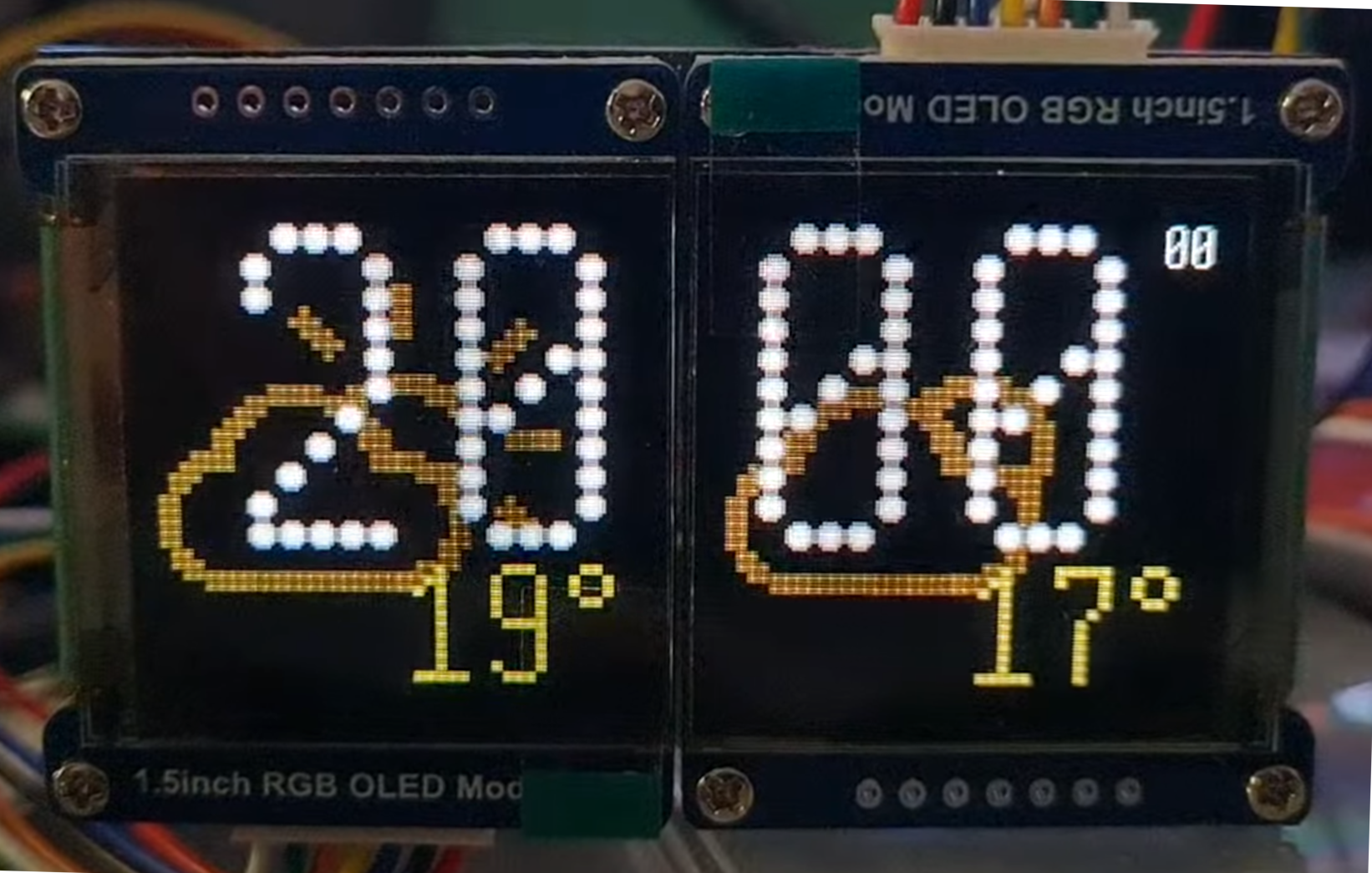
Дополнительно решил воспользоваться фоторезистором для замера окружающей освещённости, чтобы автоматически подстраивать яркость изображения под освещённость.
Платформа
Программа написана с использованием фирменного фреймворка ESP-IDF от Espresiff на чистом Си. Так же использовалась библиотека mjson для разбора принятых ответов от API сервисов. Пришлось воспользоваться сторонней даже не портированной на ESP32 библиотекой, поскольку поставляемый вместе с ESP-IDF компонент cJSON при разборе ответа прогноза погоды объёмом 16 килобайт мог потребовать больше памяти, чем было свободно в куче.
Для работы с дисплеями я написал свой собственный компонент. При написании упор был на универсальность, эффективность, лёгкость и расширяемость. Добавление виртуального экрана, изображение с которого выводится на два физических экрана одновременно, заняло несколько десятков строк. Частота кадров с учётом, что информацию надо сначала нарисовать на виртуальном экране, состаяляет примерно 58,5 кадров/сек. Компонент поддерживает так же шрифты представленные в различных форматах, типа BITSTREAM, как в библиотеках от Adafruit, а так же символы, заданные координатами точек в матрице.
Поддерживается кодировка символов Unicode, в программе могут быть загружены только необходимые наборы символов, количество наборов явно не ограничено. Компонент находится в постоянном развитии согласно моим потребностям.
Все компоненты установлены на макетной плате. Готовая плата разработчика NodeMCU-P32S установлена в кроватку, над платой находятся два дисплея. Питание осуществляется через внешний USB-C разъём. Резисторами выставлен режим потребления 5В. Дополнительна установлена кнопка для включения режима конфигурирования через веб-интерфейс и фоторезистор для подстройки яркости под окружающее освещение. Использовался готовый корпус для самодельных устройств.